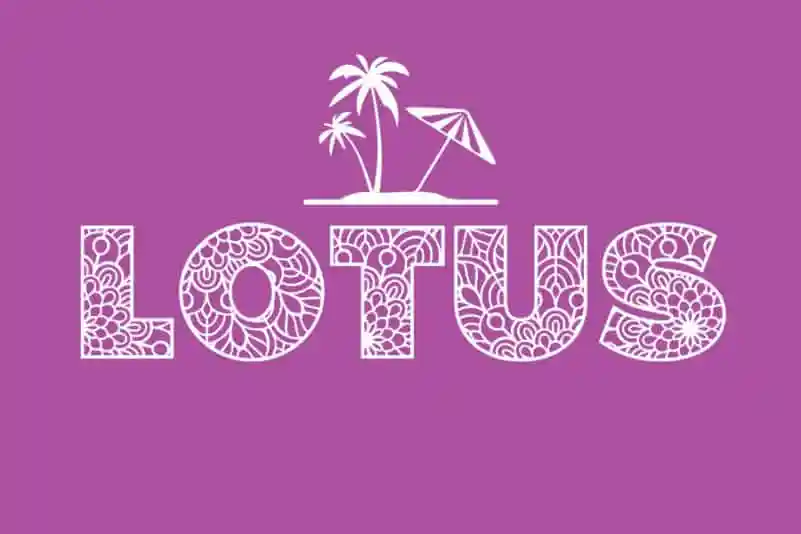
A Lotus Display Font é uma elegante escolha para aqueles que desejam imprimir personalidade e profundidade em seus projetos digitais. Esta tipografia serifada destaca-se por seu aspecto robusto e cheio, criando um efeito visual chamativo e imediato. Ideal para aplicações como design gráfico, publicidade ou mesmo websites, a Lotus Display Font oferece o poder de destacar qualquer ideia original que você possa ter. Ela é perfeita para aqueles que buscam uma fonte de exibição que não apenas chama atenção, mas também expressa um certo senso de classe e sofisticação. Para designers amadores ou experientes, a Lotus Display Font oferece a oportunidade de dar um toque diferenciado aos seus projetos. Seja você um estilista de moda, um designer gráfico ou até mesmo um fotógrafo, essa fonte é o complemento ideal para seu trabalho. Através dela, suas criações se destacarão, garantindo uma presença forte e memorável no mercado. Com sua tipografia serifada robusta, a Lotus Display Font garante que seus projetos não apenas chamem atenção, mas também transmitam um sentimento de sofisticação e confiabilidade. Escolha essa fonte para adicionar um toque único a seu próximo projeto visual.